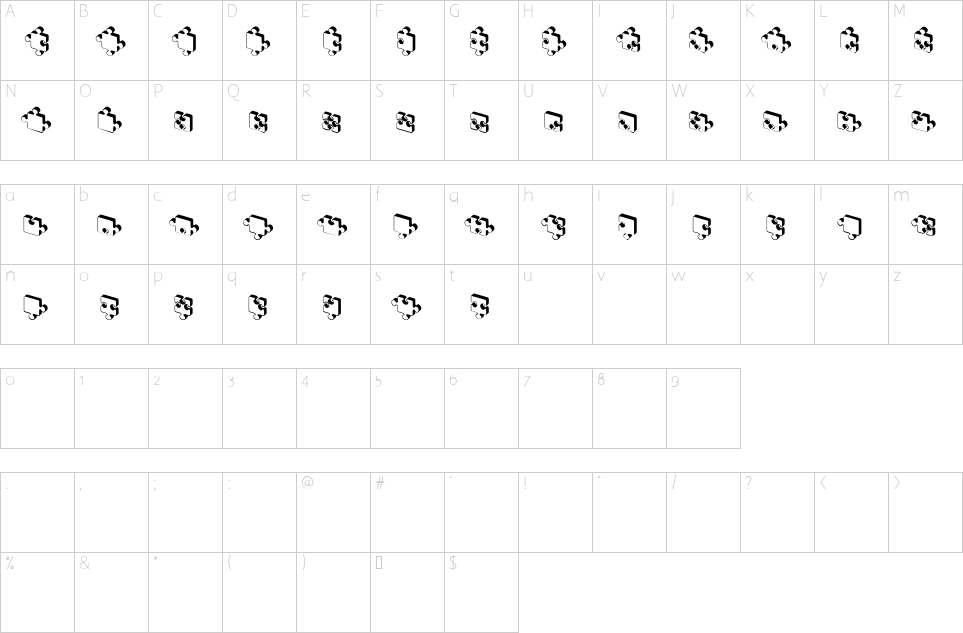
Descubra a magia dos desenhos interativos e encantadores da fonte “Jigsaw Puzzles 3D Font”. Essa elegante fonte foi criada pelo designer desconhecido Vladimir Nikolic e oferece um design incrivelmente detalhado e vibrante. O design 3D da fonte cria uma experiência de leitura única, que não apenas torna sua escrita mais interessante, mas também adiciona um toque de encanto a qualquer projeto. Confortável para uso em grandes fontes e pequenas, a fonte é perfeita para designers gráficos que buscam uma maneira criativa de fazer seus textos brilharem. Confortável para Windows e Mac, a fonte “Jigsaw Puzzles 3D” está disponível para quem busca uma opção gratuita e elegante para seus projetos, permitindo que você faça sua identidade visual mais única e memorável.